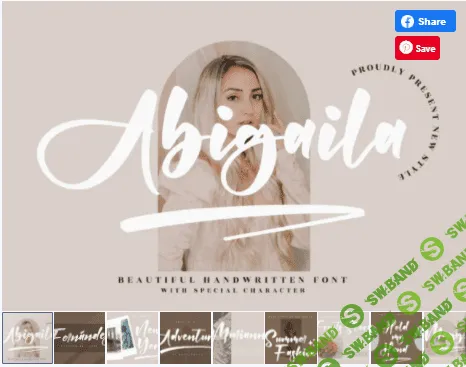
Название: Abigaila Font (2021)
[Creativefabrica] Abigaila Font (2021)
Abigaila - красивый и неподвластный времени рукописный шрифт. Это лучший выбор для создания привлекательных логотипов, брендов и цитат. Этот шрифт закодирован в кодировке PUA, что означает, что вы можете легко получить доступ ко всем глифам и штрихам!